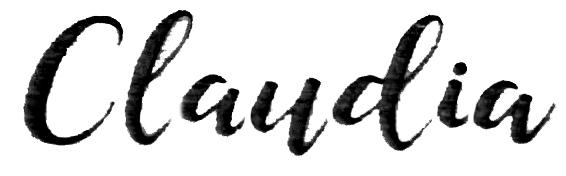
Welche Font könnte das sein?
Nachdem mir das letzte Mal hier so wahnsinnig kompetent und schnell geholfen wurde - danke nochmals! -, wäre ich euch sehr dankbar, wenn ihr euch auch diese Schrift anschauen könntet. Außer dass sie was kostet, weiß ich nichts über sie.
Die kostenlose Bromello sieht dem schon sehr ähnlich.
Da solche Fonts zur Zeit sehr im Trend sind, weshalb es nicht immer ganz einfach ist, sie zu identifizieren, kannst du dich hier, hier oder hier mal selbst nach solchen Script umsehen und dir die Fonts raussuchen, die deinen Vorstellungen entsprechen. :-D
Danke für eure Tipps! Das ist auch eine Lizenzschrift. Das ist so ziemlich das Einzige was ich darüber weiß und dass sie deutsche Sonderzeichen hat - zumindest das ü.
Der Markt ist geradezu überschwemmt mit Scripts, aber es fehlen Möglichkeiten sie bei Bedarf zu finden, weswegen ich euch damit belästigen muss, in der Hoffnung jemand kennt sie.
Diese Schrift entspricht genau den Parametern, die ich gesucht habe: verbundene Buchstaben, dick, aber nicht zu dick, verspielt, aber ohne Pinselstriche und natürlich passt die Optik und ist trotzdem sehr gut lesbar.
Ähnliche Schriften fand ich zuhauf, aber exakt diese eben nicht ;(( und nach dem Durchsuchen von tausenden Schriften, seh ich die Schriften gar nicht mehr, sondern nur mehr Pixelmus.
So, jetzt habe ich sie selbst gefunden. Ich habe das Bild bearbeitet und mit WhatFontis gesucht. Es ist die Starlight Script.
Und was die Suchmöglichkeit betrifft:
Wenn man bei Schriftsuchmaschinen wie WhatTheFont oder WhatFontIs eine verbunden geschriebene Schreibschrift finden möchte, muss man zumeist das Suchbild in einer Bildbearbeitung, wie Photoshop, Gimp und ähnlichem so bearbeiten, dass einzeln stehende Buchstaben übrig bleiben. Also jeden 2. Buchstaben weg retuschieren, hat man nur ein kurzes Wort, dies eventuell duplizieren, bei der ersten Kopie die geraden Buchstaben, und der 2. Kopie die ungeraden Buchstaben weg pinseln, dann den Bildkontrast möglichst stark erhöhen, dass möglichst nur schwarze Schrift auf weißem Grund übrig bleibt. Weiterer Bildinhalt muss auch weg.
Meist lässt sich dann tatsächlich die Schrift finden.